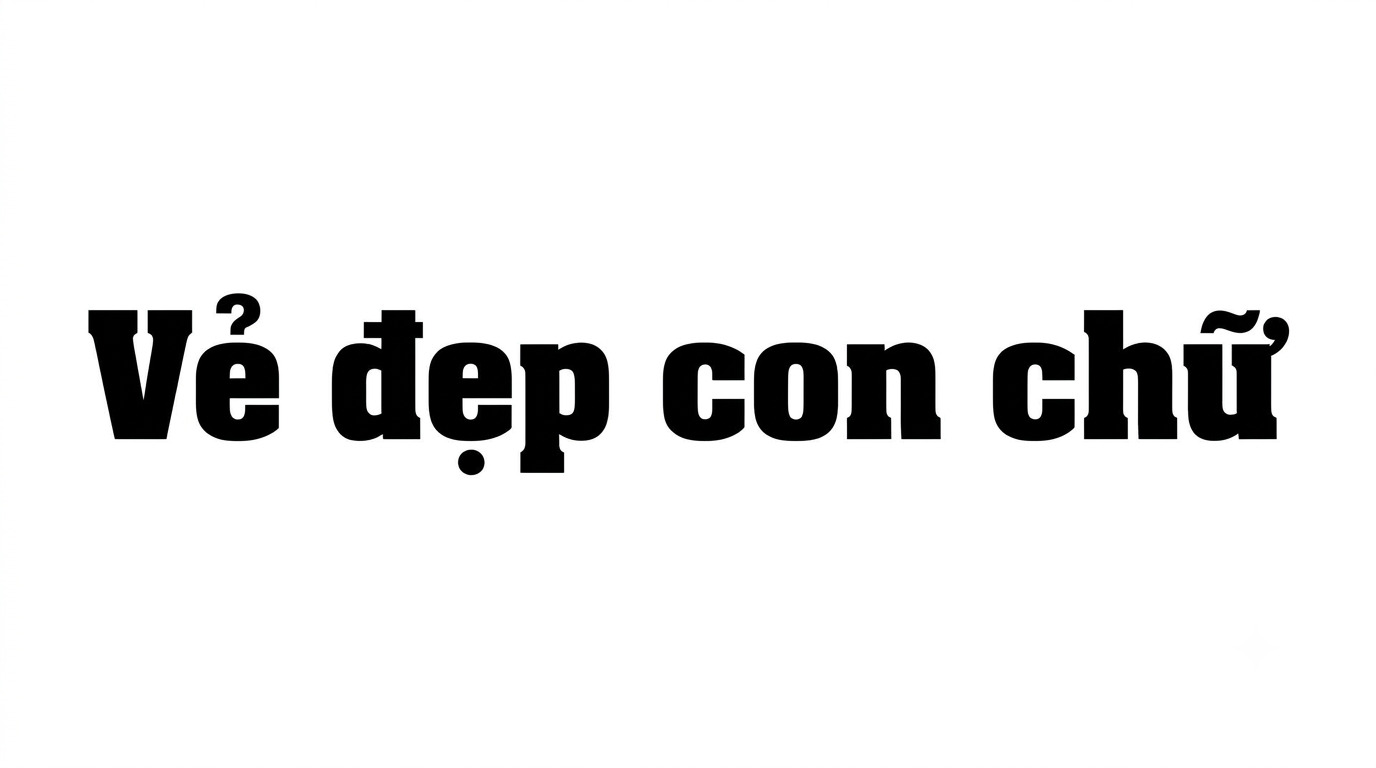
Nhiều người thiết kế khi sử dụng font Aachen gặp tình trạng thiếu ký tự tiếng Việt, dấu thanh hiển thị sai hoặc đường nét bị răng cưa khi phóng lớn để in trên hộp quà, bao bì thương hiệu. Những lỗi này làm giảm sự mạnh mẽ trong phong cách chữ, ảnh hưởng đến bố cục thiết kế và hình ảnh chuyên nghiệp của doanh nghiệp.
Font Aachen là gì?
Font Aachen là một phông chữ kinh điển thuộc dòng Slab Serif (chữ có chân lớn), được thiết kế bởi Colin Brignall và Alan Meeks. Đặc trưng nổi bật của Aachen là cấu trúc nét chữ cực kỳ vững chãi, vuông vức và mang đậm tinh thần công nghiệp, thể thao. Với độ dày nét đồng nhất và chân chữ dày, Aachen gợi lên cảm giác về sức mạnh, sự quyết đoán và bền bỉ. Đây là lựa chọn cho các thiết kế logo ngành gym, phụ tùng ô tô, thời trang nam hoặc các tiêu đề poster quảng cáo cần tạo hiệu ứng thị giác mạnh.
Tuy nhiên, phông chữ Aachen nguyên bản thường không hỗ trợ các ký tự tiếng Việt có dấu, khiến designer gặp khó khăn khi gõ các slogan hay tên thương hiệu nội địa. Bản Font Aachen Bold Việt hóa mà Xưởng In Viva chia sẻ đã được tinh chỉnh Kerning và thiết kế lại hệ thống dấu thanh cực kỳ cân đối. Việc sở hữu bộ font này giúp các sản phẩm in ấn của bạn không chỉ giữ được phong cách nguyên bản mà còn hiển thị ngôn ngữ tiếng Việt một cách thẩm mỹ, không bị lỗi nhảy chữ khi gửi file sang máy in công nghiệp.
5 Ứng dụng của font Aachen Việt hóa trong in ấn quà tặng
Nhờ phong cách mạnh mẽ, chắc chắn với cấu trúc chữ Serif đặc trưng, font Aachen Việt hóa phù hợp với các thiết kế cần thể hiện sự chuyên nghiệp, cá tính và dấu ấn riêng của thương hiệu:
• Thiết kế bao bì thực phẩm bổ sung và sản phẩm thể thao: Aachen phù hợp để in tên thương hiệu trên hộp cứng đựng Whey Protein, thực phẩm dinh dưỡng hoặc các dòng sản phẩm hướng đến phong cách sống năng động. Nét chữ dày giúp thông tin sản phẩm nổi bật trên bao bì.
• Sản xuất set quà tặng văn phòng in logo: Font Aachen Bold có thể ứng dụng để in tên doanh nghiệp, slogan trên bình giữ nhiệt kim loại, sổ tay da hoặc bút ký. Kiểu chữ khỏe khoắn giúp sản phẩm quà tặng thể hiện phong cách chuyên nghiệp, hiện đại.
• In ấn túi giấy thương hiệu cơ khí và kỹ thuật: Việc sử dụng Aachen cho logo, tên thương hiệu hoặc thông tin doanh nghiệp trên túi giấy Kraft giúp tạo cảm giác vững chãi, phù hợp với các ngành nghề như xây dựng, cơ khí, ô tô và sản xuất công nghiệp.
• Trang trí backdrop và banner sự kiện doanh nghiệp: Với định dạng vector, Aachen có thể ứng dụng cho các tiêu đề lớn trong sự kiện, hội nghị hoặc chương trình nội bộ. Cấu trúc chữ rõ ràng giúp nội dung dễ nhận diện khi trình bày ở kích thước lớn.
• Sản xuất tem nhãn decal cho máy móc và thiết bị: Độ dày của Aachen giúp các thông tin như mã sản phẩm, tên thiết bị hoặc ký hiệu kỹ thuật hiển thị rõ ràng trên tem nhãn, phù hợp với các sản phẩm thuộc lĩnh vực công nghiệp.
5 lưu ý khi sử dụng font chữ Aachen Việt hóa
Để thiết kế sử dụng font Aachen Việt hóa đạt độ sắc nét và phù hợp khi đưa vào sản xuất thực tế, designer nên chú ý các yếu tố kỹ thuật sau:
• Kiểm soát độ dày nét chữ: Aachen có cấu trúc chữ đậm với phần chân Serif rõ nét. Khi in logo hoặc tem nhãn kích thước nhỏ, nên lựa chọn kích thước chữ phù hợp để các chi tiết không bị dính vào nhau do ảnh hưởng của mực in.
• Cân chỉnh khoảng cách ký tự (Kerning): Các ký tự của Aachen có hình khối, vì vậy khoảng cách giữa từng chữ cần được điều chỉnh thủ công khi thiết kế logo hoặc slogan. Điều này giúp bố cục chữ cân đối hơn trên hộp quà, túi giấy hoặc sản phẩm quà tặng.